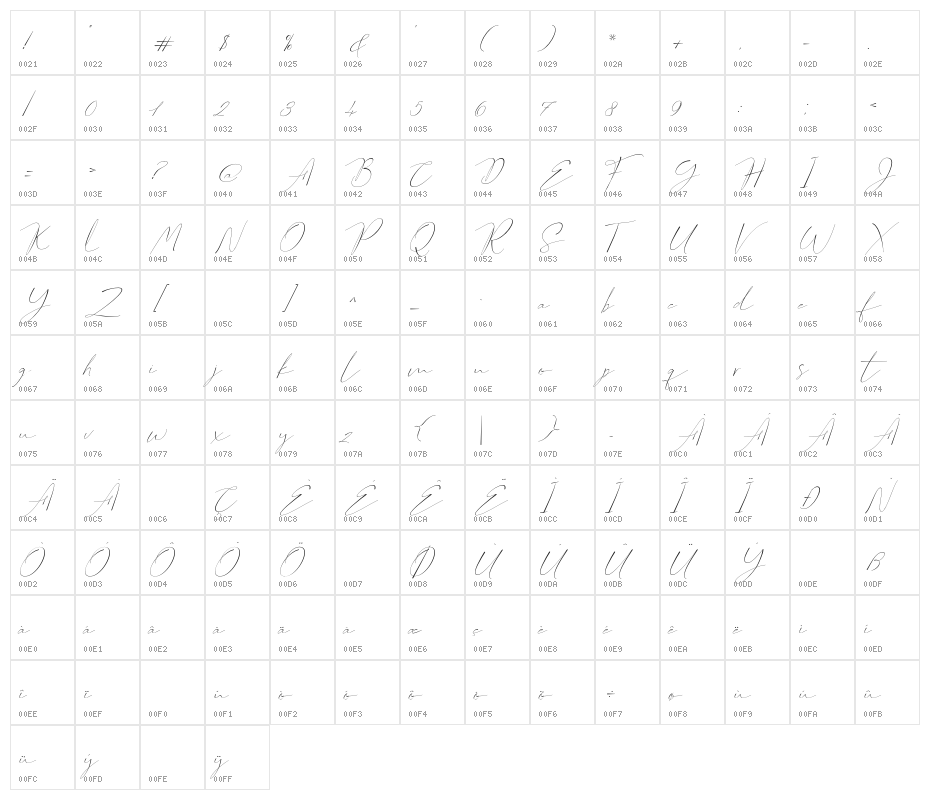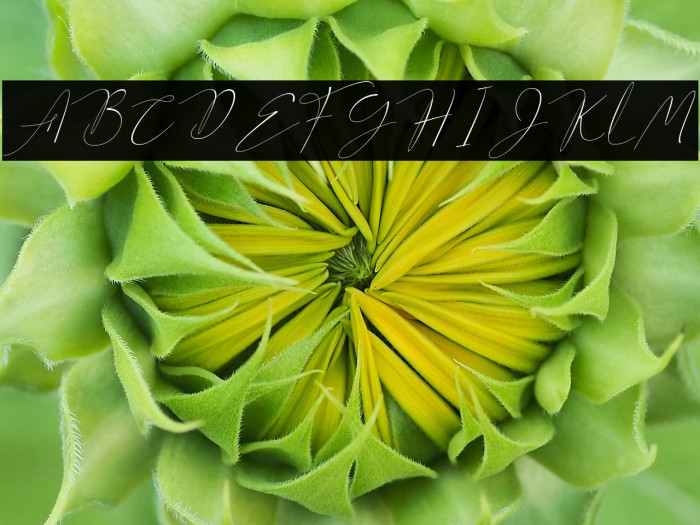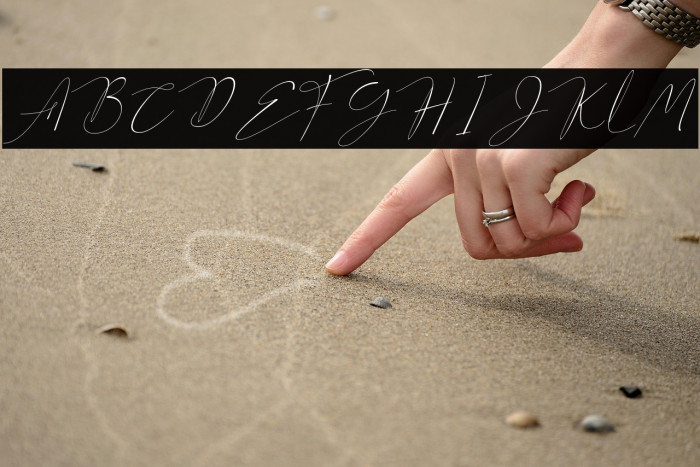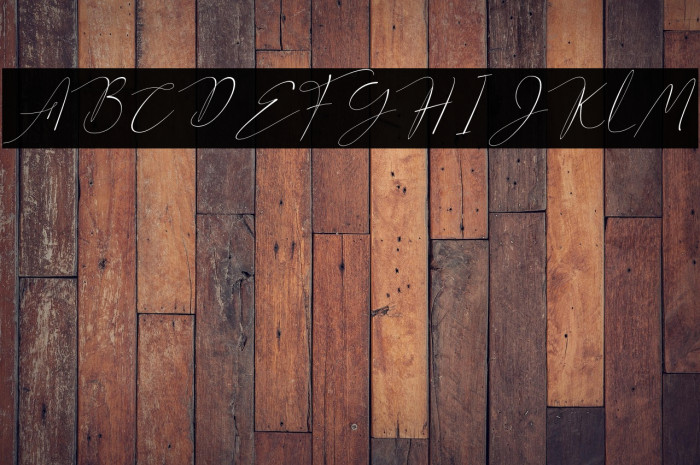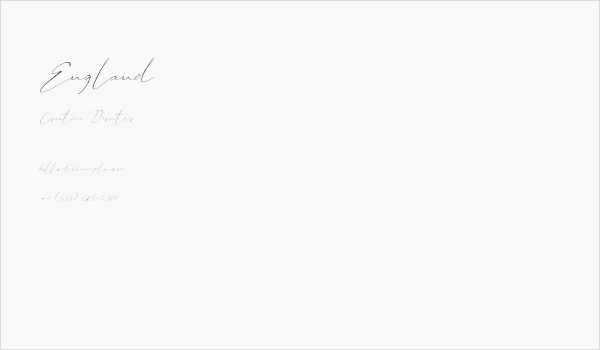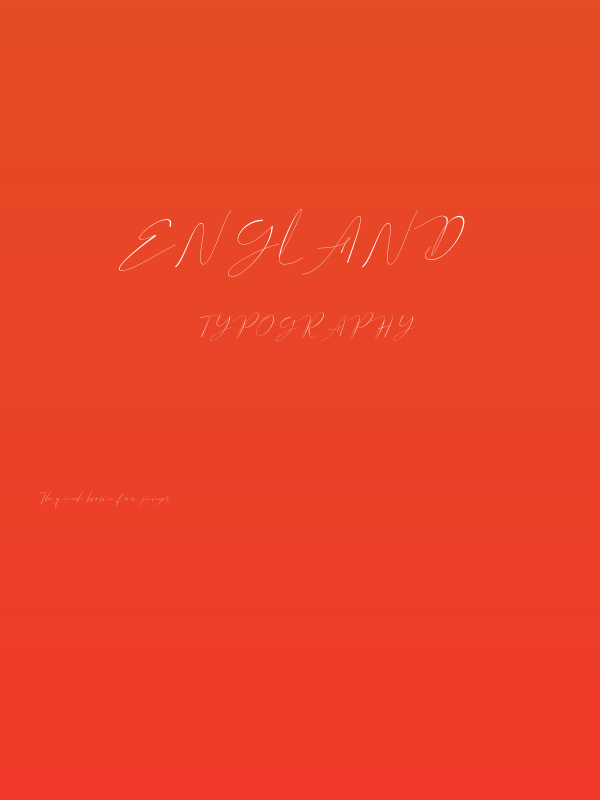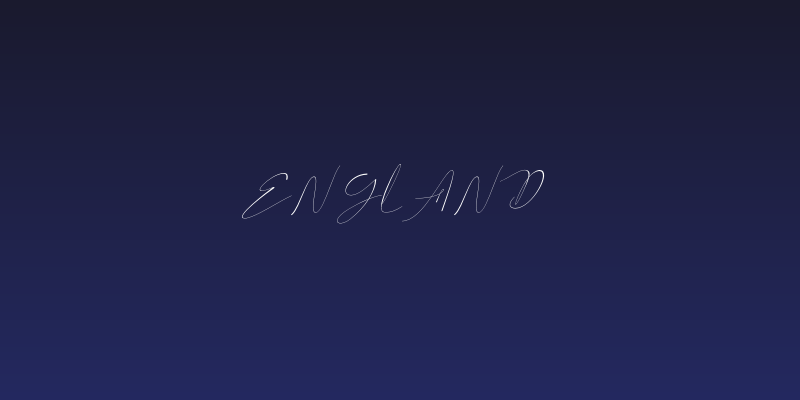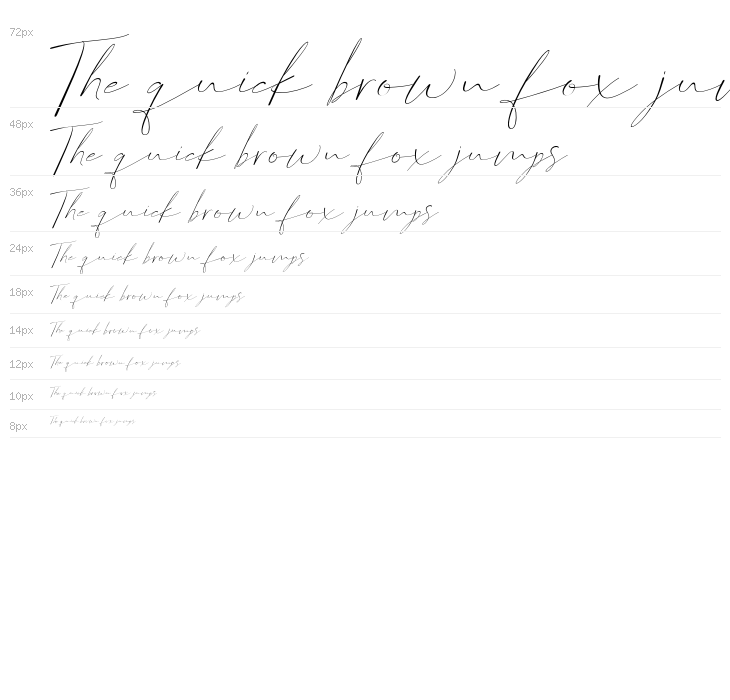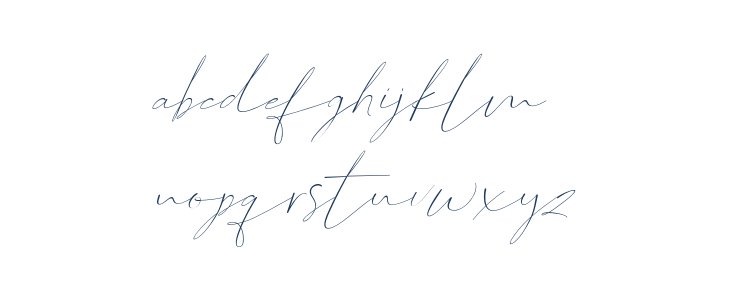
England Font
✎ Script
| Kategorien | Script |
| Gesamtstil | Elegant |
| Anwendungsfall | Logos, Invitations, Branding |
| Vorgeschlagene Projekte | Ideal for wedding invitations, elegant branding, personal stationery, and upscale packaging. |